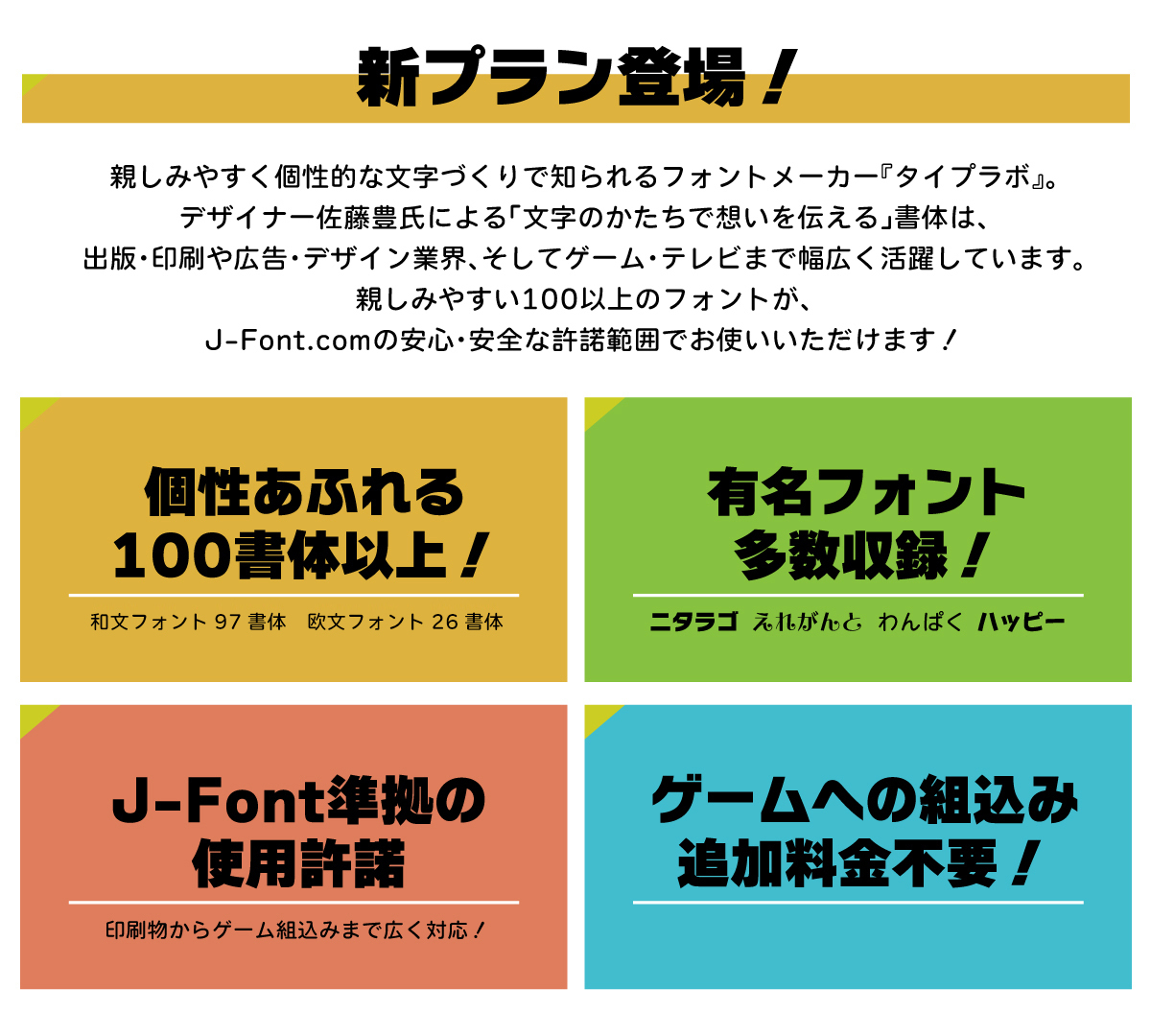
タイプラボは、親しみやすく個性的な文字づくりで知られるフォントメーカーです。
デザイナー佐藤豊氏による「文字のかたちで想いを伝える」書体は、
出版・印刷や広告・デザイン業界、そしてテレビ・映像制作まで幅広く活躍しています。
佐藤 豊 Satoh Yutaka
1951年、東京下町生まれ。
1986年、第9回石井賞創作タイプフェイスコンテスト第1位。
1987年、第2回モリサワ国際タイプフェイスコンテスト欧文部門第2位。
1996年、第5回モリサワ国際タイプフェイスコンテスト和文部門金賞。
これまでに、あられ・えれがんと・キャピー・ハッピー・墨東・わんぱく・ニタラゴ・ルイカ・セプテンバーなどのフォントを制作している。